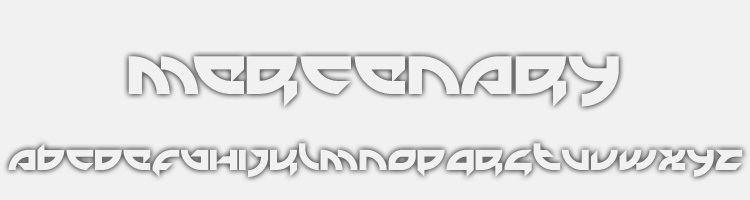
Mercenary od Defaulterror to darmowy, futurystyczny font typu display o surowym, sci-fi charakterze. Litery zbudowane są z ciężkich, geometrycznych łuków i zdecydowanych cięć, przełamanych ostrymi nacięciami i przekątnymi, co nadaje całości mechaniczny, zakodowany i lekko agresywny wyraz.
Dzięki temu Mercenary naturalnie sprawdza się w logotypach gier, plakatach wydarzeń technologicznych, okładkach albumów, grafikach streamingowych i tytułach, gdzie krótkie słowa wymagają wyrazistego, syntetycznego brzmienia. Jako darmowy font, doskonale nadaje się również do monogramów i nagłówków, ponieważ duże, obłe kształty i ścięte rogi tworzą odważną sylwetkę nawet przy użyciu zaledwie kilku znaków.
Mercenary powstał podczas projektowania logo Augment. Schmaak it broken!